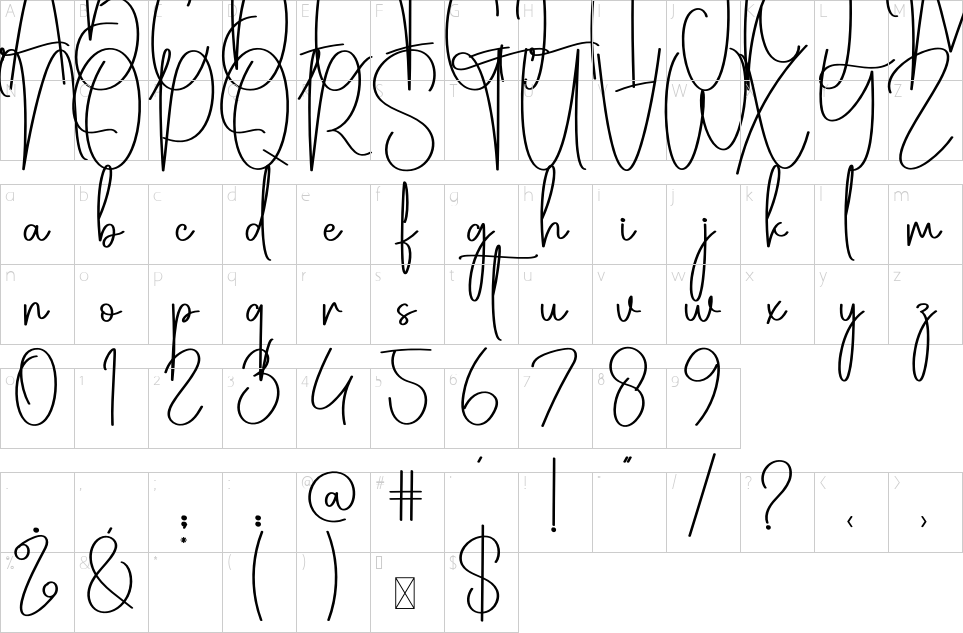
Mugshots Font | 1001 Free Fonts – Download Grátis
Descubra Mugshots, uma fonte grátis que combina elegância e originalidade para tornar seus materiais de texto um verdadeiro trabalho de arte. Com 1001 Free Fonts, você tem a oportunidade de experimentar uma ampla variedade de fontes gratuitas, incluindo Mugshots. Desenvolvida por scratchones, esta font é projetada para dar um toque único e moderno a qualquer projeto. Com sua interface intuitiva, Mugshots é fácil de usar, permitindo que você personalize seu design de acordo com suas necessidades. Com 438 downloads, é evidente que a qualidade e a variedade desta font agradam os usuários. Para quem busca uma maneira fresca de dar vida a suas criações digitais, Mugshots é um excelente escolha, e é perfeitamente compatível com os sistemas operacionais Windows e Mac. Download hoje e descubra como Mugshots pode tornar suas páginas um verdadeiro show de cores e texturas.